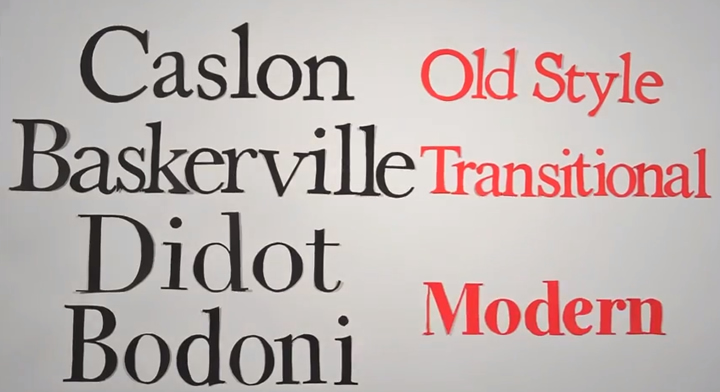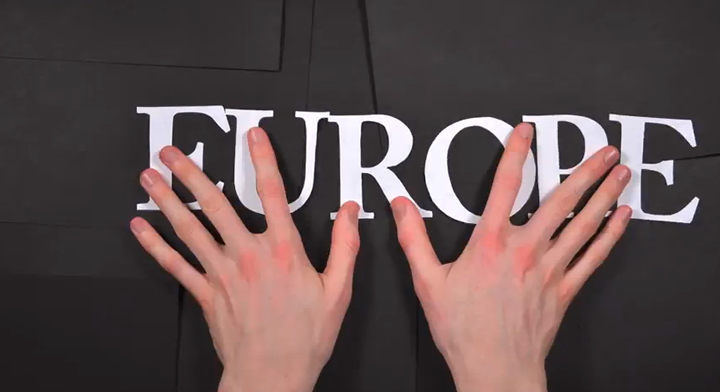
Un vaste sujet qu’est la typographie. Certaines personnes l’abordent en long en large et en travers pour au final se rendre compte qu’il est impossible de rapidement connaitre toutes les subtilités liées à ce sujet.
Ce petit court métrage réalisé par Ben Barrett-Forrest, est le fruit de 140 heures de travail, 2454 photographies et 291 lettres de papier découpées. Un travail imposant et une réalisation intéressante pour une vidéo retraçant rapidement l’historique de la typographie.
Par exemple on apprend (ou on conforte son opinion) que le créateur de la typographie est l’allemand Johannes Gutenberg dans les années 1450. Il a créer la typographie Blackletter. Suite à cela, pour des soucis de compréhension et de lisibilité, est arrivé la typographie de type « Roman » apparue au 15ème siècle créée par Nicolas Jenson (qui a été l’un des influencer de Mr Garamond).
Après le succès de la Roman, c’est au tour de l’italic… Sans parler de vide, l’histoire de la typographie est assez pauvre jusqu’au 18ème siècle en Angleterre. William Caslon, Baskerville, Didot ou encore Bodoni ont révolutionné les styles avec chacuns leurs particularités.
Suite à cela, nous avons vu les typographies se différencier par types, styles et autres déclinaisons. Avec l’avancement du temps, les lettrines se sont allongées, grandies, grossies avec aujourd’hui des typographies plus ou moins fantaisies.